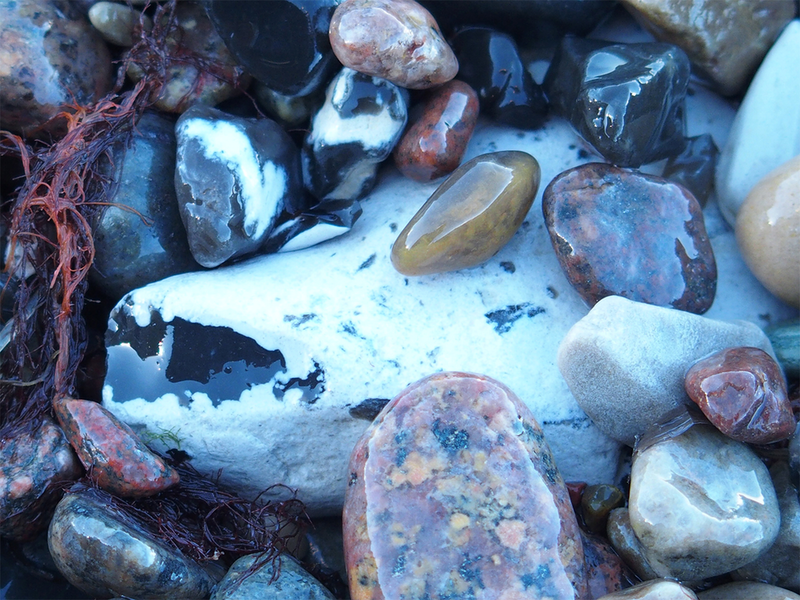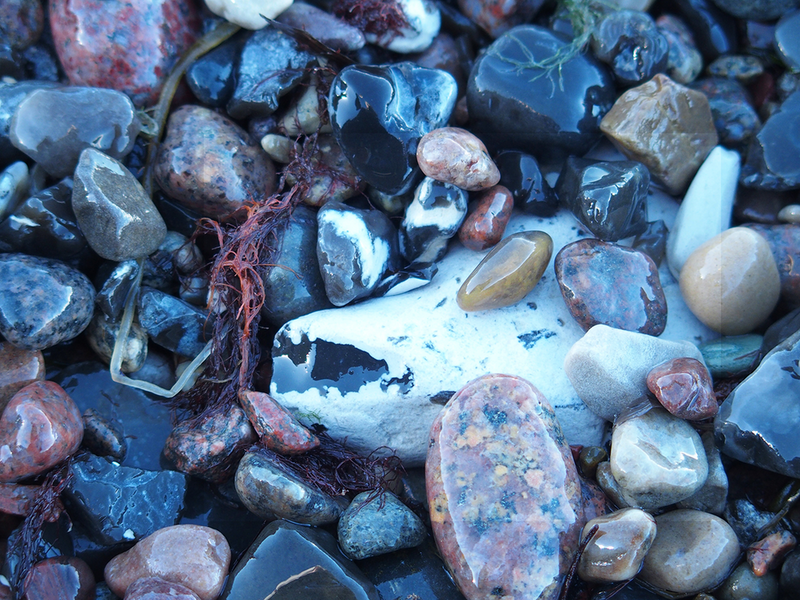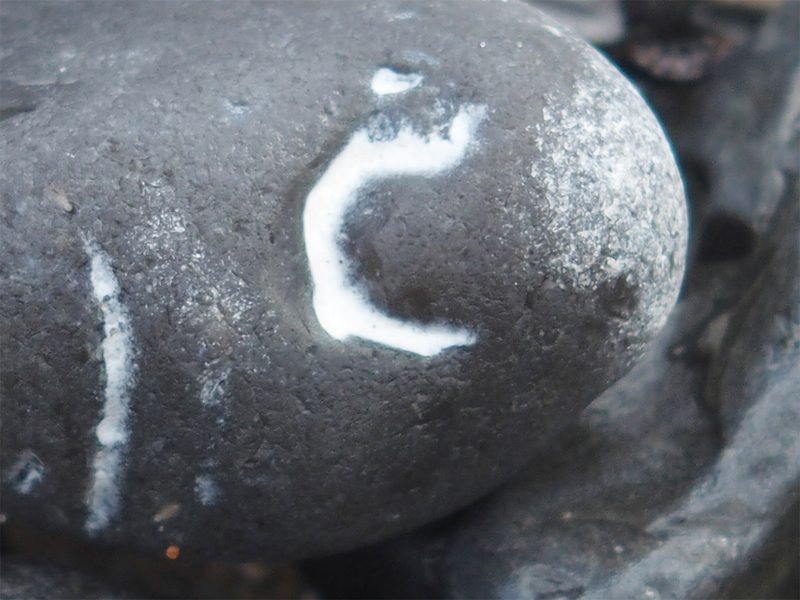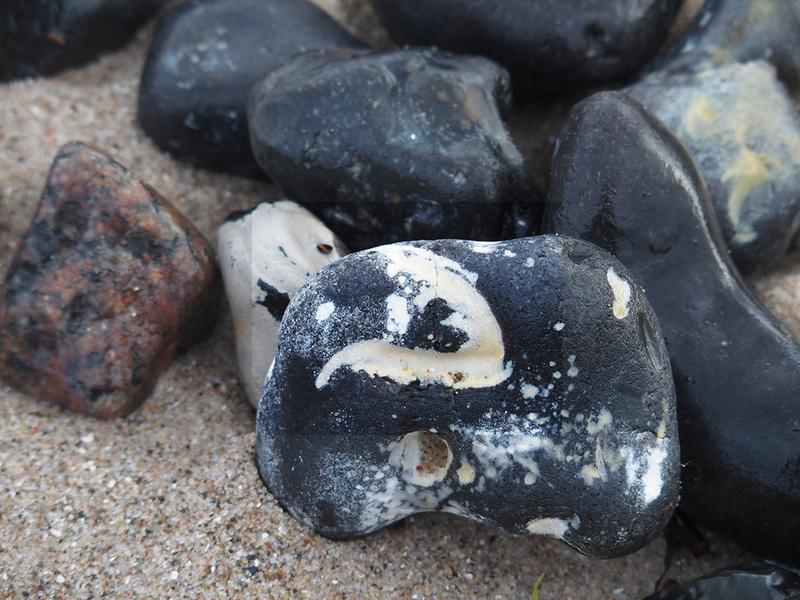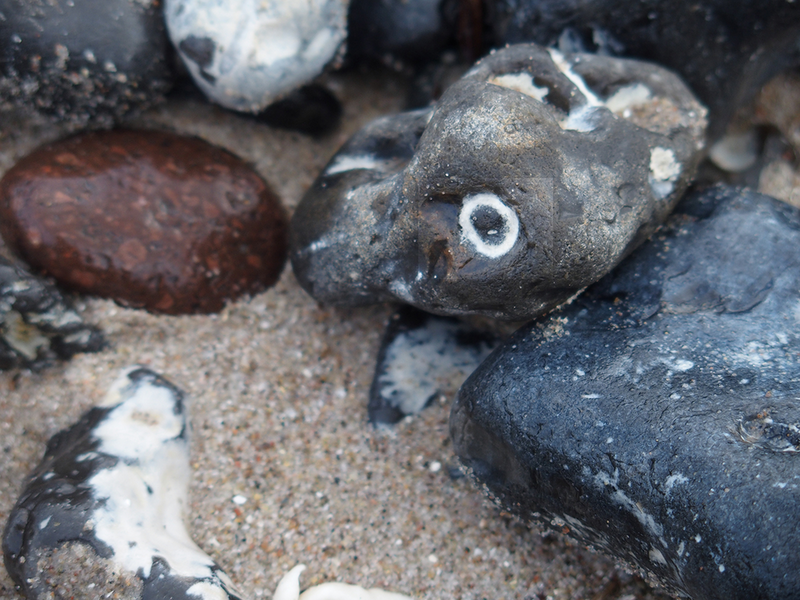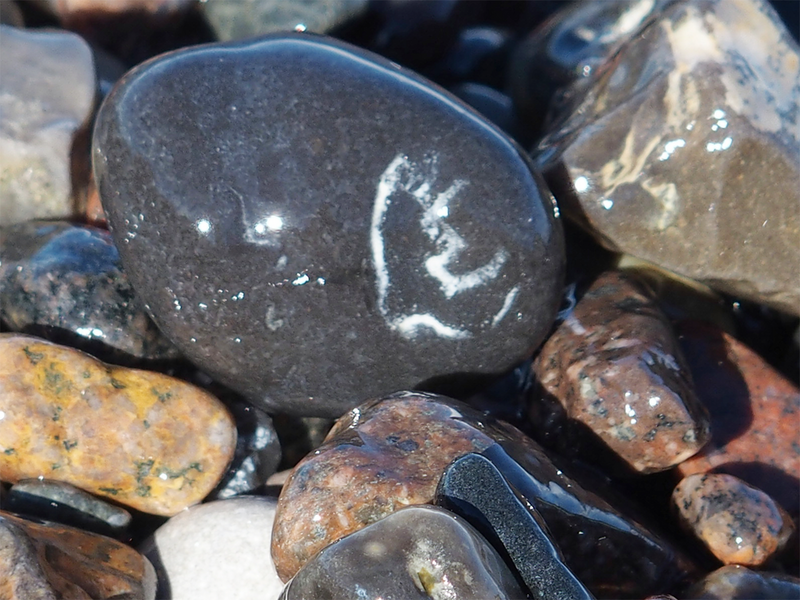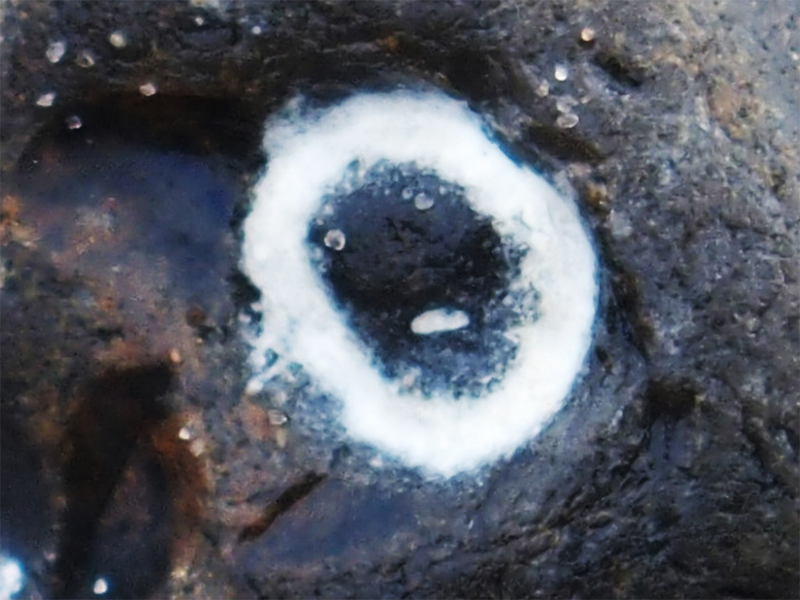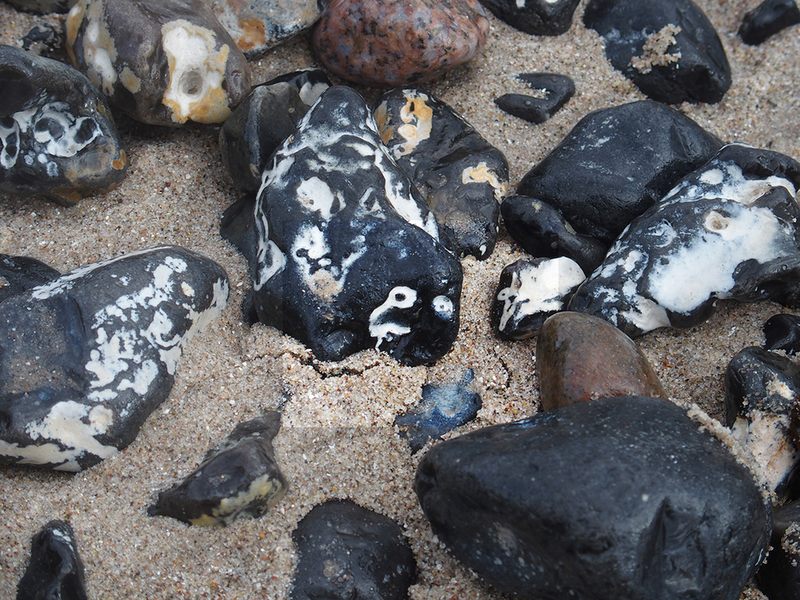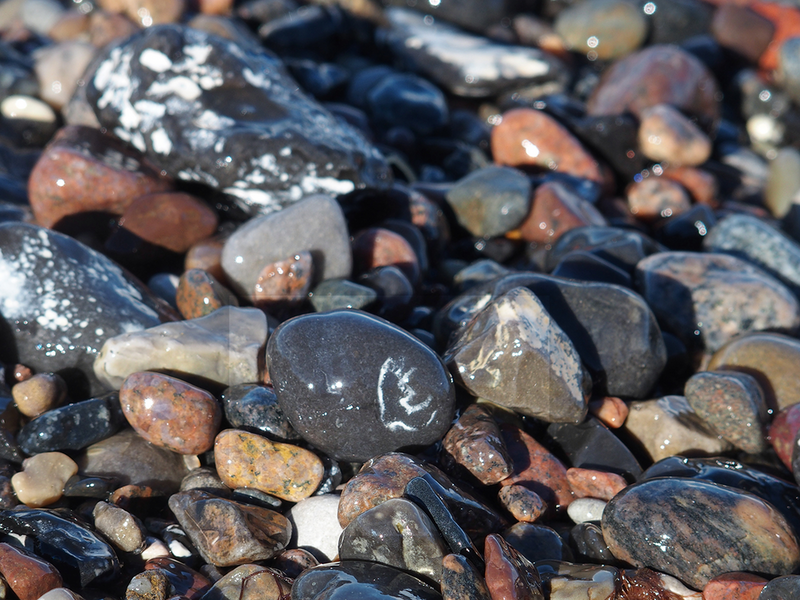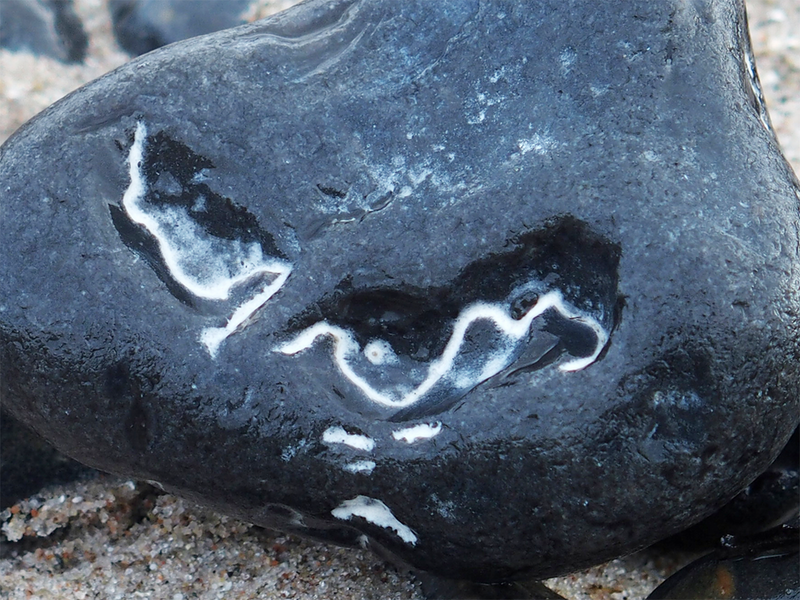
Ostseetypografie Teil 4 - Stein-Typografie Teil 2
Auch im Herbst 2016 habe ich am Stand von Mukran (auf der Insel Rügen) wieder Steine gesammelt. Leider war gerade eine kleine Sturmflut und man bekam nasse Füße beim Aufnehmen der Steine.
Aber hier sind immer viele Steine mit verschiedensten Zeichnungen zu finden. Natürlich sind die Buchstaben und Zeichen auf den Steinen nicht mehr als eine Laune der Natur von Meer und Wind. Trotzdem lassen sich bestimmte Buchstabenformen sehr gut erkennen.
Hier die typografischen Steine vom Herbst 2016: